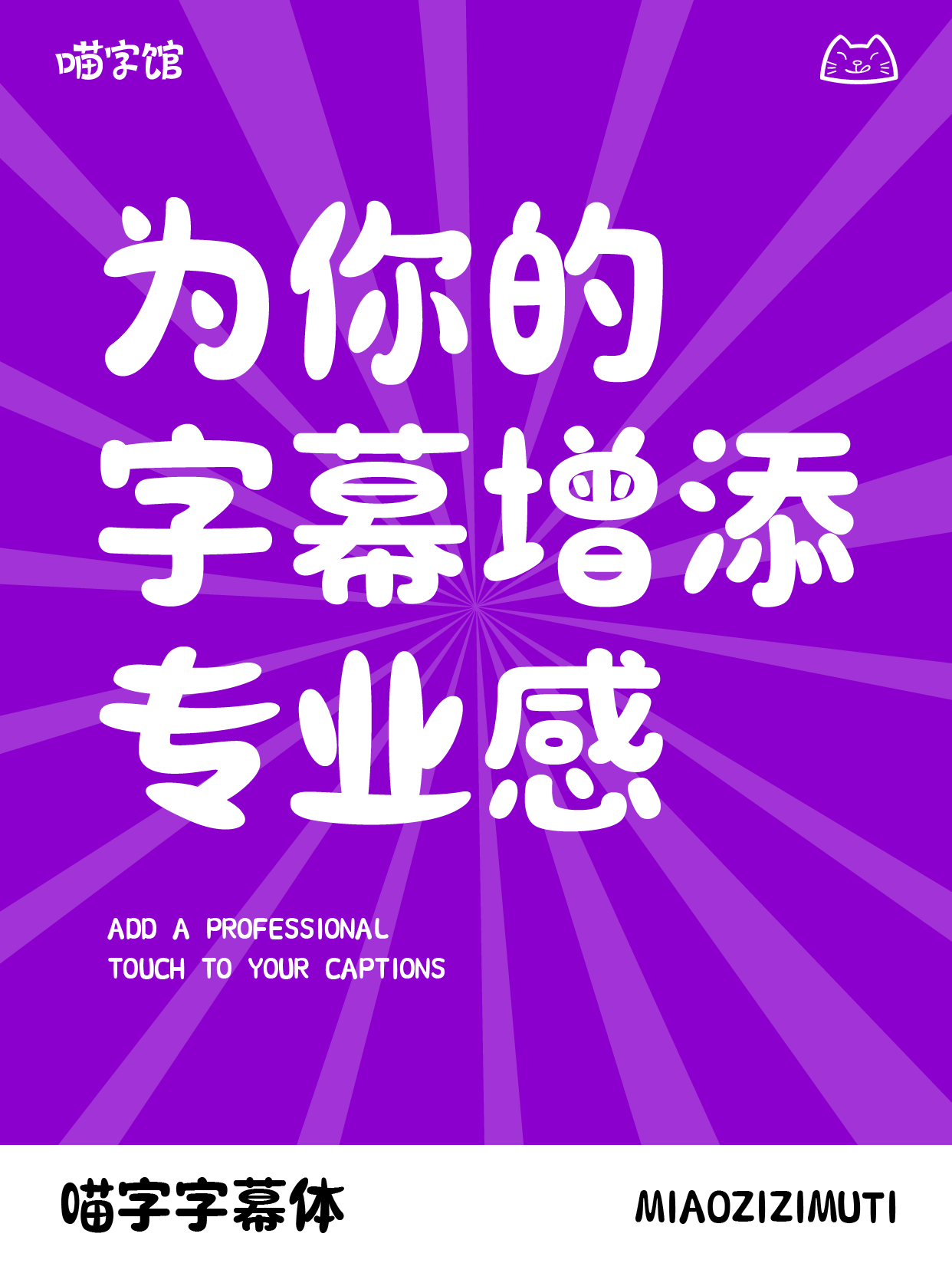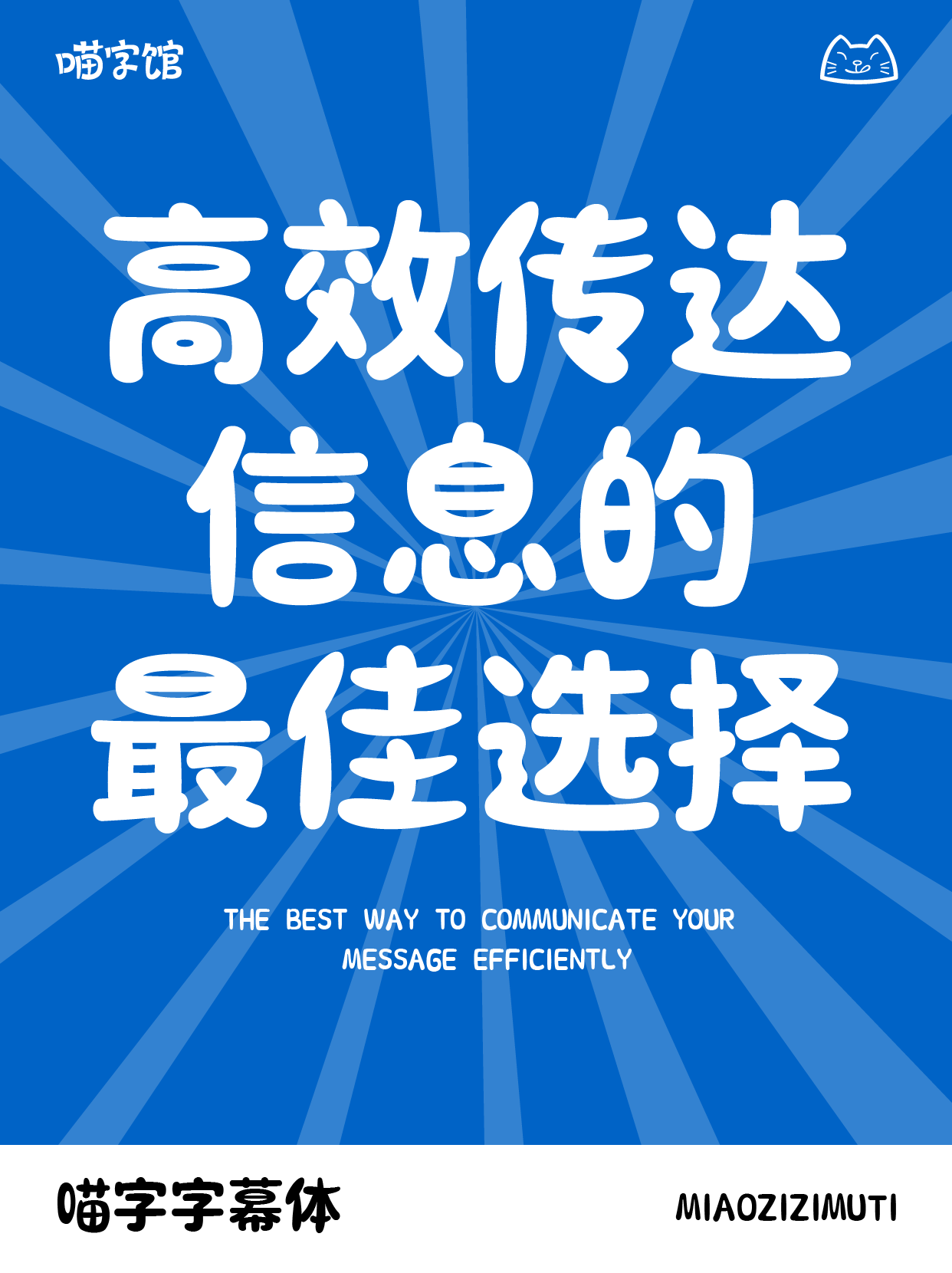
喵字字幕体
MiaoZiZiMuTi
先快乐,其他的再说。
喵字字幕体,是一款专为新媒体行业所量身打造的定制级细分字库。这款字库旨在为新媒体内容创作者提供最贴合当下需求的字体解决方案。其设计精髓在于融合了现代感与易读性的双重考量,字形设计大胆开放,摒弃了严肃路线,突破了传统字库的拘束感,巧妙地加入了符合数字屏幕阅读习惯的年轻化元素。